Ширина прописных: букв: Г, Е, З, С; А, Д, М, Х, Ц, Ы, Ю; Ж, Ф, Ш, Ъ; Щ; Б, В, И, К, Л, Н, О, П, Р, Т, У, Ч, Ь, Э,Я Ширина строчных букв: э, с а, м, ц, ъ ,ы, ю ж, т, ф, ш, щ | 5/10h 7/10h 8/10h 9/10h 6/10h 4/10h 6/10h 7/10h 8/10h 5/10h | 1,3 1,8 2 2,2 1,5 1 1,5 1,8 1,3 | 1,8 2,5 2,8 3,2 2,1 1,4 2,1 2,5 2,8 1,8 | 2,5 3,5 4 4,5 3 2 3 3,5 4 2,5 | 3,5 5 5,6 6,3 4,2 2,8 4,2 5 5,6 3,5 | 5,0 7 8 9 6 4 6 7 8 5 | 7,0 10 11,2 12,6 8,4 5,6 8,4 10 11,2 7 | 14 16 18 12 8 12 14 16 10 |
Методические указания по дисциплине Инженерная графика, по теме “Шрифты чертежные”
Шрифты чертежные
Чертежи и прочие конструкторские документы содержат необходимые надписи чертежным шрифтом :
– основная надпись
– размеры на чертежах
– обозначения видов и разрезов
– технические требования
– схемы структурные
– схемы принципиальные
– перечень элементов
– спецификация
ГОСТ 2.304-81 устанавливает чертежные шрифты для всех чертежей, схем и текстовых документов.
Мы изучаем шрифт типа Б с наклоном 75 градусов
т.2 5 т.3
получаем угол 75 градусов
т.1
Образец наклона отрезка прямой под углом 75 градусов
(без применения транспортира)
В инженерной графике все размеры в мм, поэтому ставим только цифровое значение размера.
5 , 20 — значение в мм т.1 — точка 1
В конспекте вы работаете с бумагой в клетку. Помните одна клетка – 5 мм
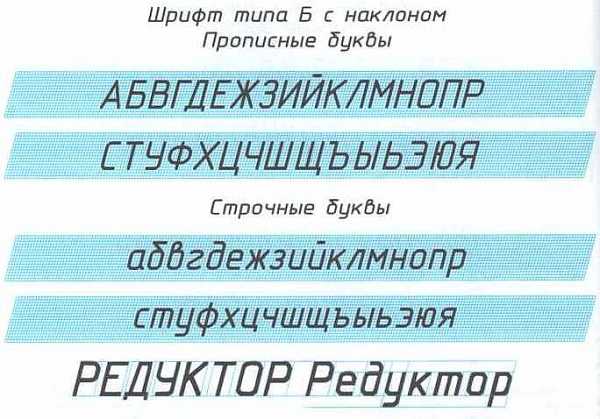
Рис.1
Рассмотрите внимательно прописные буквы, строчные буквы и расстояния между буквами. Чертежный шрифт очень прост в написании. Все буквы состоят из одинаковых элементов (модулей).
Вспомните прописи 1 класса. Сравните наклон букв в прописях. Угол одинаковый 75 градусов. Это значит, что вы с этим углом наклона знакомы с 1 класса.
Размер шрифта это высота h прописных букв в миллиметрах.
Толщина линии шрифта d зависит от размера шрифта: (1/10)h для шрифта типа Б.
На учебных чертежах и при заполнении основной надписи мы будем применять
следующие размеры шрифта: 2,5; 3,5; 5; 7; 10.
Для скорейшего освоения написания текста чертежным шрифтом необходимо освоить начертания основных модулей, из которых состоят все буквы чертежного шрифта.
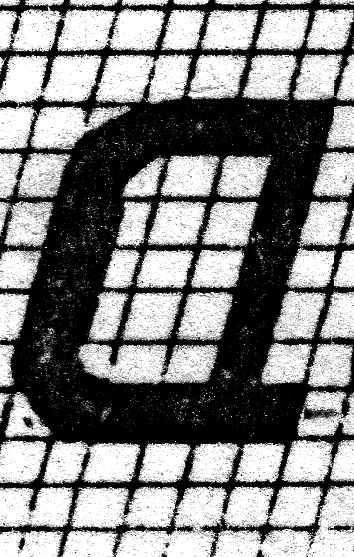
Входит только в букву а
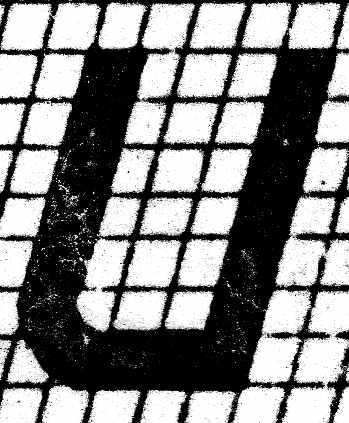
Входит в буквы : й, ц, ш, щ, у. т, п (повернуто на 180 град.)
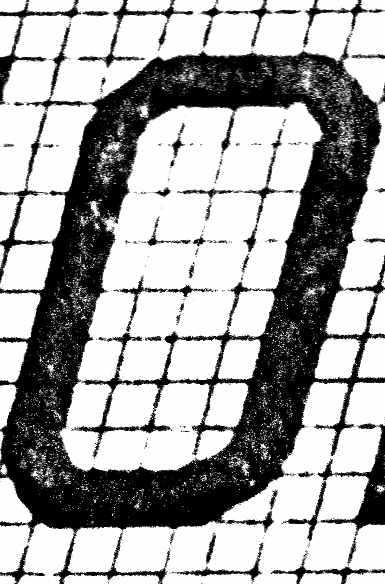
Входит в буквы б, в, д, ю
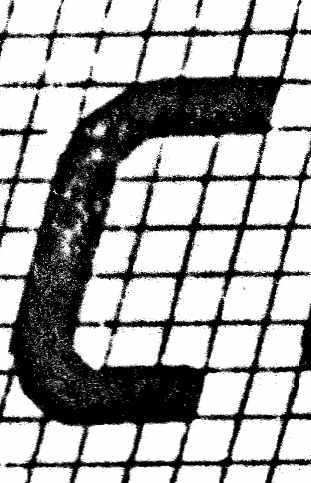
Входит в буквы е, ф, я
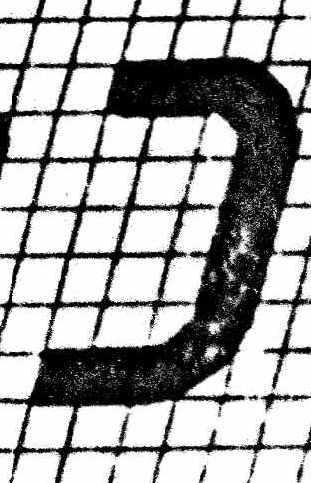
Входит в буквы р, ф, ъ, ы, ь
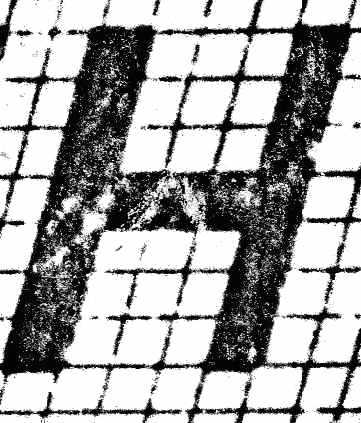
Входит во все буквы для соблюдения параллельности между
двумя соседними линиями, кроме наклонных (А, Л)
В конспекте выполнить 6 строк модулей высотой 5 мм (1 клетка).
Шрифт типа Б (d=h/10)
Таб.1
вспомогательной сетки)
b
(17/10)h
17d
4.3
6.0
8.5
12.0
17.0
24.0
34.0
Минимальное расстояние между словами
е
(6/10)h
6d
1.5
2.1
3.0
4.2
6.0
8.4
12.0
Толщина линий шрифта
d
(1/10)h
d
0.25
0.35
0.5
0.7
1.0
1.4
2.0
Написание текста чертежным шрифтом № 20 производится путем вычерчивания внешнего и внутреннего контура букв и цифр с соблюдением величины d (толщина линий шрифта) твердым карандашом на миллиметровке, а затем закрашиванием мягким карандашом расстояние между двумя контурами.
Написание текста чертежным шрифтом №10 и меньше производится мягким не заточенным карандашом единым движением руки (часть конструкции буквы)
Написание текста чертежным шрифтом №5 и меньше производится твердым заточенным карандашом единым движением руки (часть конструкции буквы)
Упрощенное расстояние между словами чертежного шрифта №10 и меньше берется из расчета ширины строчной буквы н
Стр.5
Ширина букв и цифр
Таб.2
hТипа Б
Прописные буквы
Б, В, И, Й, К, Л, Н,О, П, Р, Т, У, Ц, Ч, Ь, Э, Я, Ъ
а, б, в, г, д, е, и, к, л, м, н, о, п, р, у, х, ц, ч, ь, э ,я
(5/10)
м, ъ, ы, ю
(6/10)
ж, т, ф, щ, ш
(7/10)
с, з
(4/10)
Цифры
2, 3, 5, 6, 7, 8, 9, 0
(5/10)
4
(6/10)
1
(4/10)
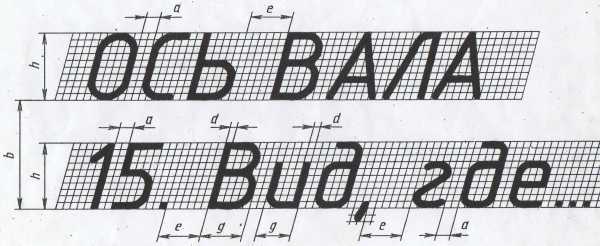
Рассмотрите надписи и сравните буквенные значения с таблицей 1.
Какое буквенное значение вы не нашли в таблице 1?
Теперь прочтите заголовок таблицы 2. Какое назначение таблицы 2?
Приложение
Шрифты чертежные ГОСТ 2.304-81
Шрифт типа Б с наклоном 75 градусов